上首斗金体,简体中文约6763字,字体笔画刚柔相济端庄优雅,整体的断口设计使其风格更加国潮风。适用于搭配标志、广告标语、商业广告等高端属性。
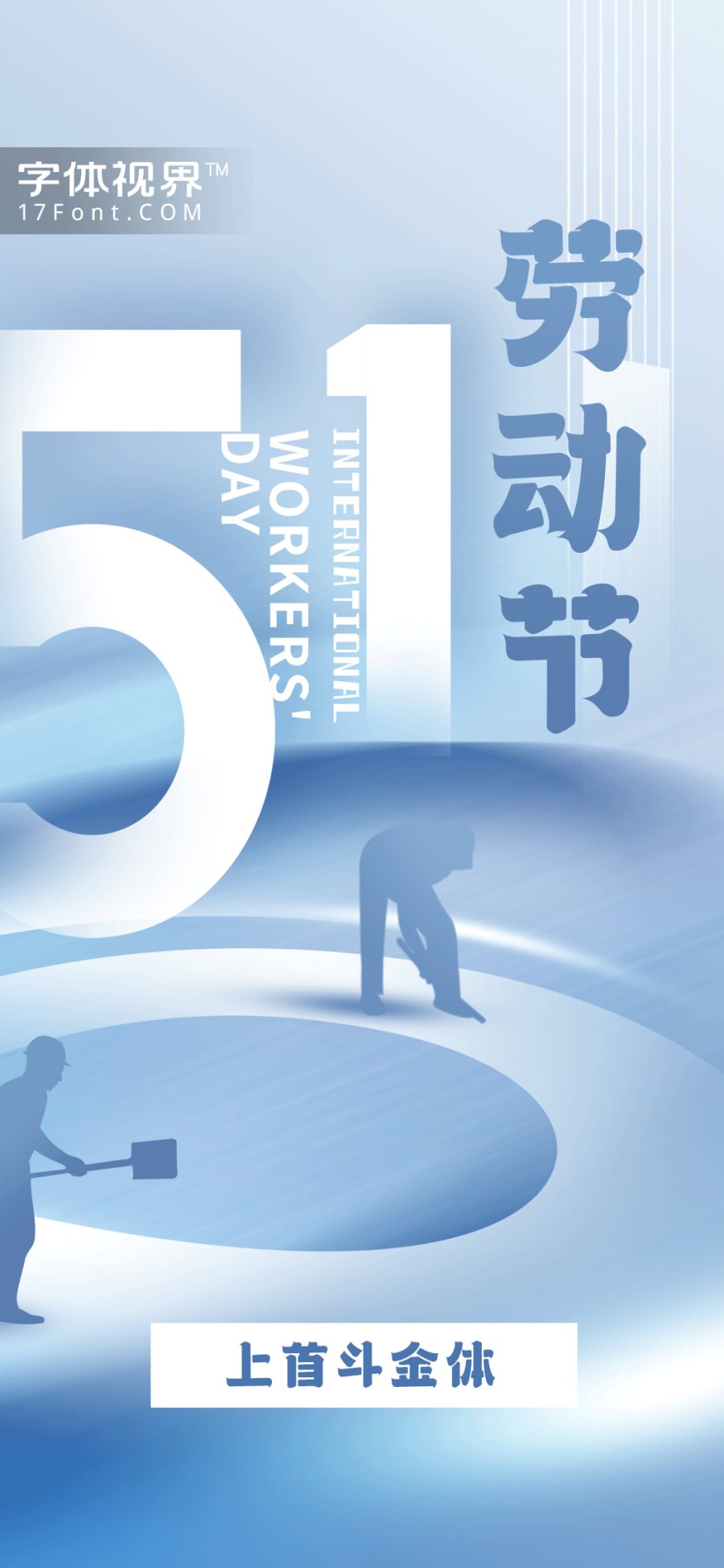
上首豆干体,字体笔画粗细对比强烈,横竖笔进行了改良,整体直线处理,字体笔画简洁,整体具有创意风格,个体笔画形态苍劲有力特点。 适用于搭配标志、广告标语、商业广告等。